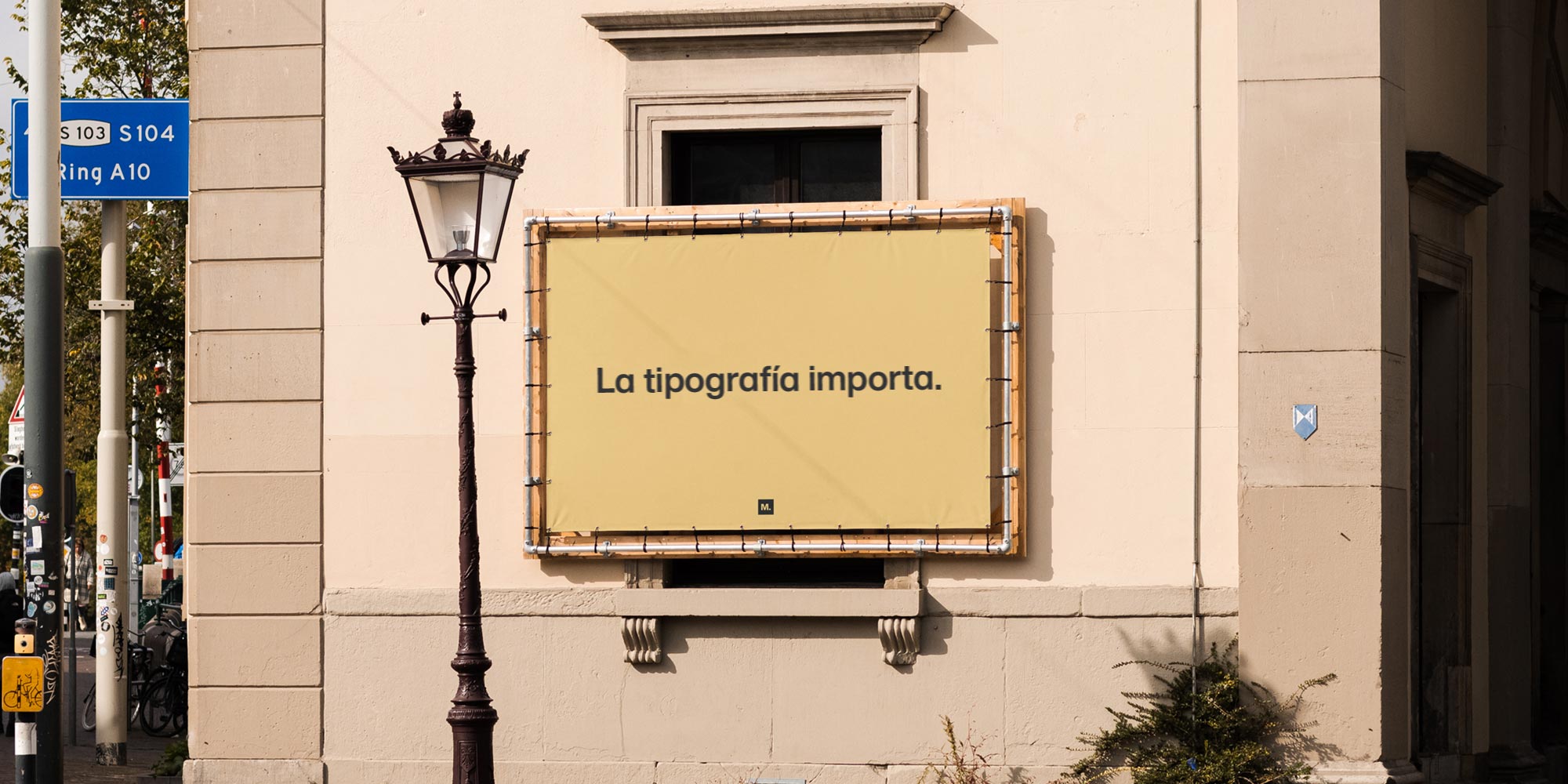
La tipografía importa: Un nuevo estudio revela que el impacto emocional de las fuentes varía en función del país
• El estudio neurocientífico de Monotype revela que los distintos estilos de fuente evocan respuestas emocionales diferentes según el país
• La investigación aporta nuevas perspectivas sobre la tipografía y las distintas respuestas emocionales que causan en ocho países: Alemania, Australia, España, Estados Unidos, Francia, Japón, Portugal y Reino Unido.
• Los resultados, presentados en el nuevo informe, «Typography Matters: How to Leverage Neuroscience to Build a Memorable Brand» («La tipografía importa: Cómo utilizar la neurociencia para crear una marca que destaque»), son de lectura obligatoria para las marcas, los equipos creativos y las organizaciones que desarrollan campañas de información para el público.
WOBURN (Massachusetts), 11 de diciembre de 2023. Monotype, líder mundial en tipografía y tecnología, ha publicado un nuevo estudio que revela que la respuesta emocional a las fuentes varía significativamente de un país a otro. Este estudio en curso, pionero en su género, se ha realizado en colaboración con Neurons, una empresa de neurociencia aplicada. Los resultados revelan el impacto emocional que provocan las fuentes y los matices culturales de las respuestas que se dan en ocho países diferentes: Alemania, Australia, España, Estados Unidos, Francia, Japón, Portugal y Reino Unido.
Al probar tres tipos de letras distintas, los investigadores descubrieron que, aunque la elección del tipo de letra desempeña un papel fundamental a la hora de provocar respuestas emocionales, la preferencia por unas fuentes u otras y su impacto varían significativamente según el contexto cultural y la ubicación geográfica.
«Las diferencias visibles en los resultados del Reino Unido y de Francia nos muestran hasta qué punto dos culturas próximas geográficamente pueden reaccionar de forma distinta ante la tipografía y el lenguaje», señala Damien Collot, director creativo de tipografía de Monotype en Francia. «Para marcas que crean campañas publicitarias y organizaciones que llevan a cabo campañas de información pública, comprender desde un punto de vista científico cómo varía la respuesta emocional en función de la elección de la fuente en las distintas regiones y lenguas puede ser clave para generar vínculos más profundos y significativos con el público» .
El punto de encuentro entre el arte y la ciencia
Monotype lleva desde 2021 investigando el poder que ejercen los tipos de letras en nuestras respuestas emocionales, así como la forma en que transmiten emociones, moldean percepciones e influyen en las identidades de marca. Las últimas conclusiones dan nuevas pautas al mundo del marketing profesional para adaptar las estrategias creativas y de marca a las distintas regiones, teniendo en cuenta las diferencias culturales y lingüísticas.
Conclusiones principales del informe aplicables a todas las regiones:
• Fuentes dinámicas con remate: los tipos de letras con remate, como Cotford, transmiten honestidad y calidad. Las asociaciones culturales de las fuentes con remate las convierten en una opción atractiva para las marcas que pretenden evocar estas emociones.
• Letras de palo seco humanistas: fuentes como FS Jack pueden plasmar innovación y distinción. El diseño de FS Jack, con raíces en la caligrafía, suele provocar respuestas emocionales relacionadas con el protagonismo y la innovación.
• Letras de palo seco geométricas: los tipos de letras como Gilroy Bold se asocian con la honestidad y la claridad. Gilroy transmite bien estos atributos, sobre todo en los textos más largos.
• El tamaño, el color y el espaciado de la tipografía influyen en cómo se percibe.
Aspectos culturales
El informe pone de manifiesto que las elecciones tipográficas y las respuestas emocionales varían según la lengua y la cultura. Aunque los y las profesionales de la creación y el diseño suelen tener un sexto sentido para prever la respuesta emocional que causarán las fuentes que eligen, esta intuición suele estar influenciada por sus propias experiencias culturales y lingüísticas. Este informe recalca lo importante que es investigar las diferencias regionales en la interpretación y percepción de la tipografía a la hora de elegir una fuente para campañas internacionales de marketing y marca.
Conclusiones principales sobre los diversos países:
• Las preferencias por determinados tipos de letras y las asociaciones emocionales varían sustancialmente según el idioma y la familia lingüística. Ser conscientes de este hecho es muy útil para responsables de marketing de las marcas, especialistas de la creación y organismos públicos.
• Las personas encuestadas de los países anglófonos (Australia, Estados Unidos y Reino Unido) mostraron preferencia por las características peculiares en los tipos de letras.
• Las de España, Francia y Portugal, regiones con una extensa historia de imprenta y que han sido testigos de la rápida difusión de las tipografías móviles en Europa, mostraron una preferencia significativa por el estilo de remate clásico y sentimental de Cotford.